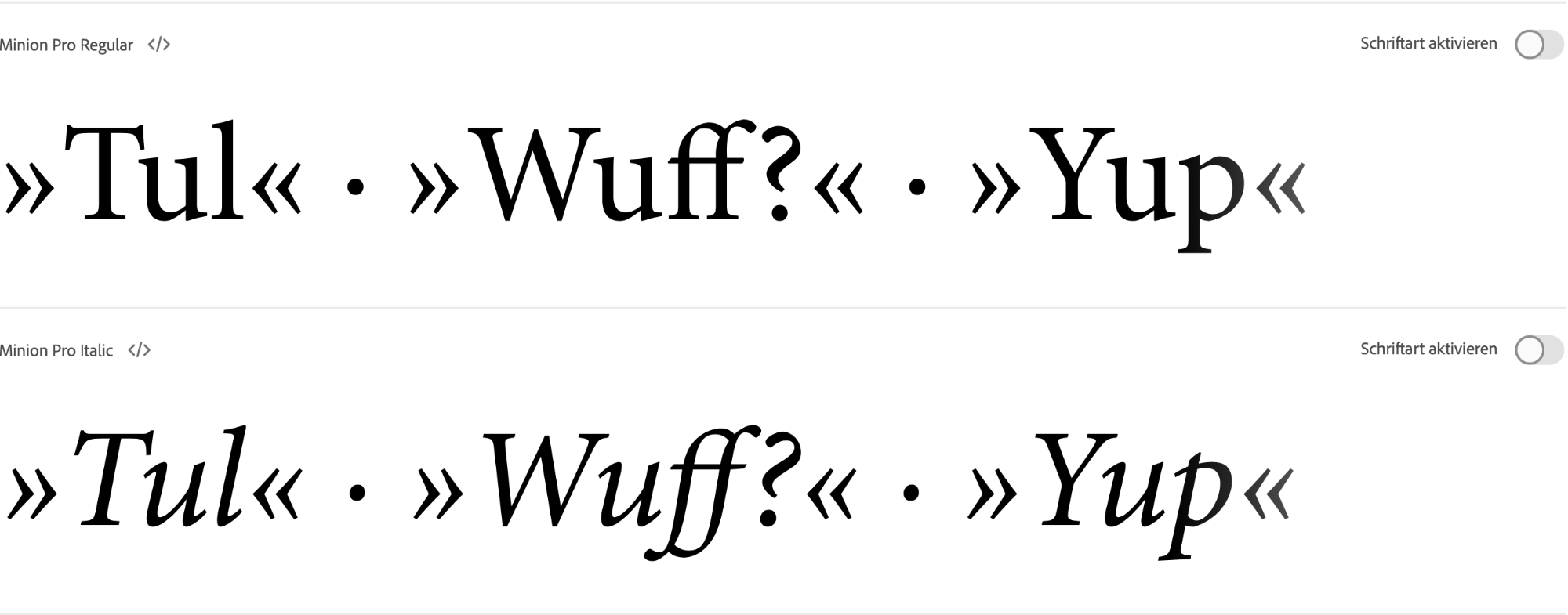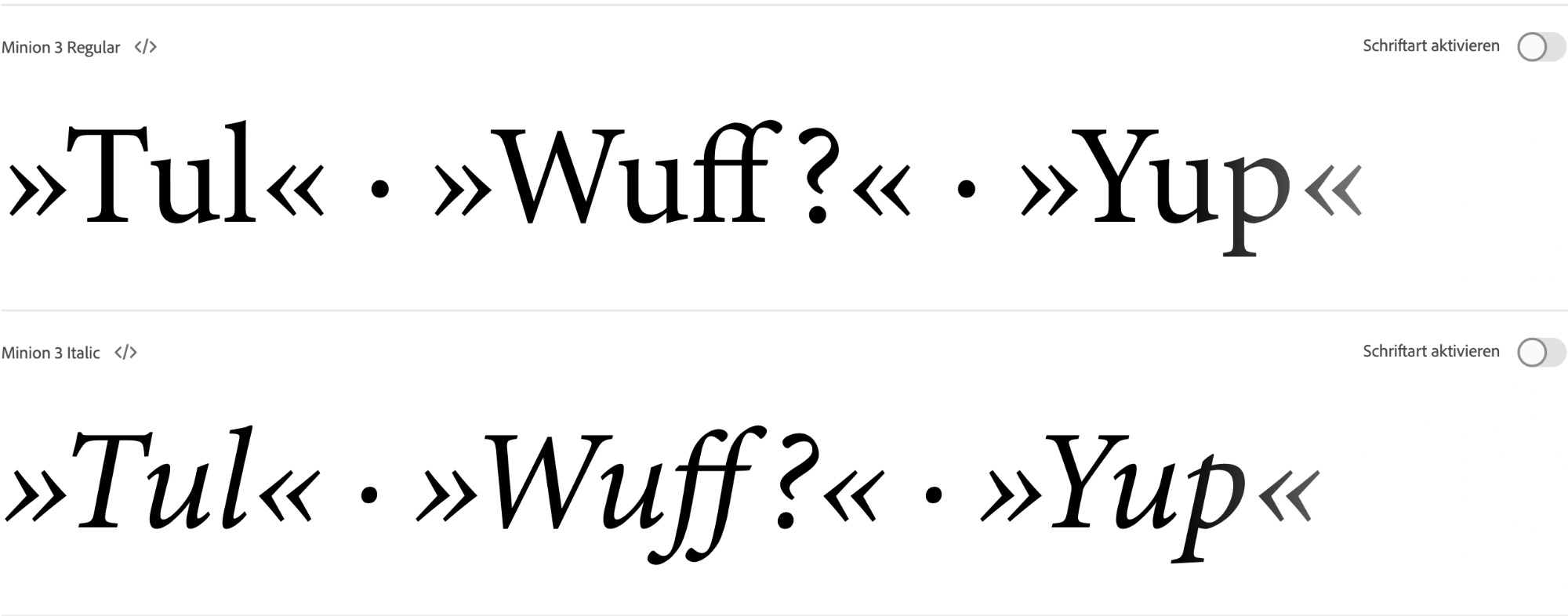
schon seit längerem interessiere ich mich für die Agmena. Für den Satz (geistes)wissenschaftlicher Texte scheint sie mir nicht minder geeignet als für jenen "literarischer". Liege ich da falsch? Leider habe ich die Schrift, von einem kurzen Klappentext abgesehen, noch nirgends in gedruckter Form gesehen. Kann mir vielleicht jemand Titel von aus der Agmena gesetzten Büchern nennen?
Auch würde mich interessieren, wie gut das "mitgelieferte" Kerning der Schrift ist, insbesondere jenes statistisch häufiger Unterschneidungspaare (etwa solcher für die diversen deutschen und englischen Interpunktionszeichen.)
Ich frage dies, weil ich typographischer Laie bin, der für diesbezügliche Verbesserungen weder die Zeit noch die notwendige Software hat (von der erforderlichen Expertise ganz zu schweigen ... ).
Um einen groben Anhaltspunkt meiner diesbezüglichen Qualitätsansprüche zu geben: Ich finde beispielsweise das Kerning der Minion 3 durchaus zufriedenstellend, jenes der Minion Pro hingegen vielfach ärgerlich.
Auch würde mich interessieren, wie gut die Schrift unprofessionellen Laserdruck übersteht, der bei mir den unvermeidlichen Regelfall darstellt. Meine derzeitigen "Arbeitspferde", Minion 3 und Minion Math, mit denen ich ansonsten höchst zufrieden bin, schauen auf von Laserdruckern mit Auflösungen von 600 und 1200 dpi  ausgeworfenen Blättern leider arg beleidigt aus. Ist die Agmena hier toleranter?
Please find below the same questions in German:
-------------------------
Sehr geehrte Damen/Herren,
ich trage mich mit dem Gedanken, eine Lizenz Ihres Fonts Agmena zu erwerben.
Da ich weder Jurist noch „vom Fach“ bin, habe ich zuvor zu Ihrer EULA, deren rechtliche Konsequenzen mir weitgehend unklar sind, noch einige Fragen.
Ich beabsichtige den Font ausschließlich in nicht-editierbaren Pdf-Dokumenten zu verwenden, und zwar in folgender Weise:
(1)   für Preprints, Beamer-Präsentationen und Handouts, die ich auf meiner persönlichen Website jedem Besucher unentgeltlich und unbeschränkt als Downloads zugänglich mache;
(2)   für Preprints, Beamer-Präsentationen und Handouts, die auf der Website einer Konferenz, einer „Sommerschule“ oder eines akademischen „Workshops“ unentgeltlich und unbeschränkt als Downloads zugänglich sind;
(3)   für Diplomarbeiten und Dissertationen, die auf dem Server einer Universitätsbibliothek der Allgemeinheit zum kostenlosen Download zur Verfügung gestellt werden (als „echte“ Pdfs, nicht als Scans von Papiervorlagen);
(4)   für Bücher, die von kommerziellen Verlagen bzw. Book-On-Demand Services
(4.a) in Papierform und/oder
(4.b) im nicht-editierbaren Pdf-Format (als Downloads vom Server des Verlags) entweder
(4.b.e) entgeltlich  oder auch
(4.b.u) unentgeltlich („Open Access“)
vertrieben werden.
Welche der Verwendungsweisen (1) bis (4.b.u) sind durch die EULA gedeckt? Welche potentiellen „legalen Fallstricke“ gibt es bzgl. der unter (4) zusammengefaßten Punkte?  Benötigt bei letzterer Verwendung etwa auch der Verlag eine Lizenz, wie teuer ist eine solche, etc. ?
Stimmt, das ist mir auch schon aufgefallen, habe aber nie mit einer anderen Minion verglichen. Danke fürs Zeigen.
Stimmt, das ist mir auch schon aufgefallen
Danke für die Bestätigung.  Ich vermute, daß der gefälligere Eindruck der Minion 3 hier auch etwas (wenn nicht sogar gänzlich) mit den etwas anders gezeichneten, »breiteren« Guillemets zu tun hat.